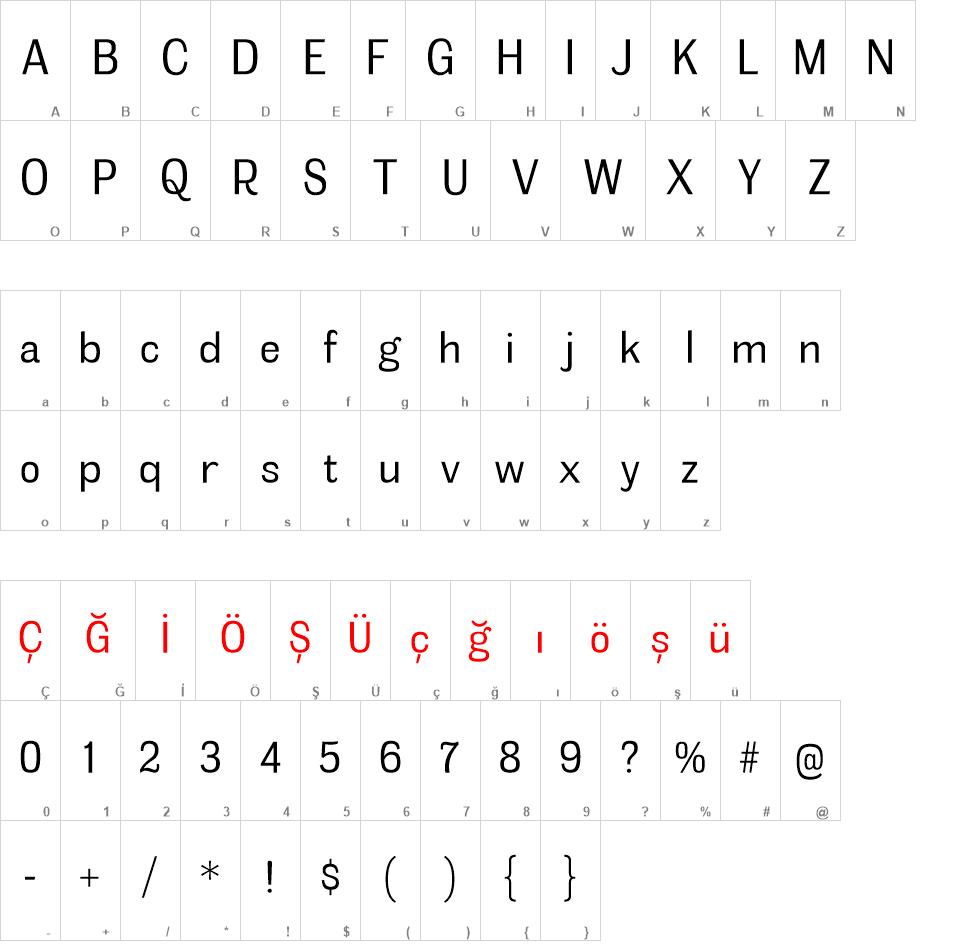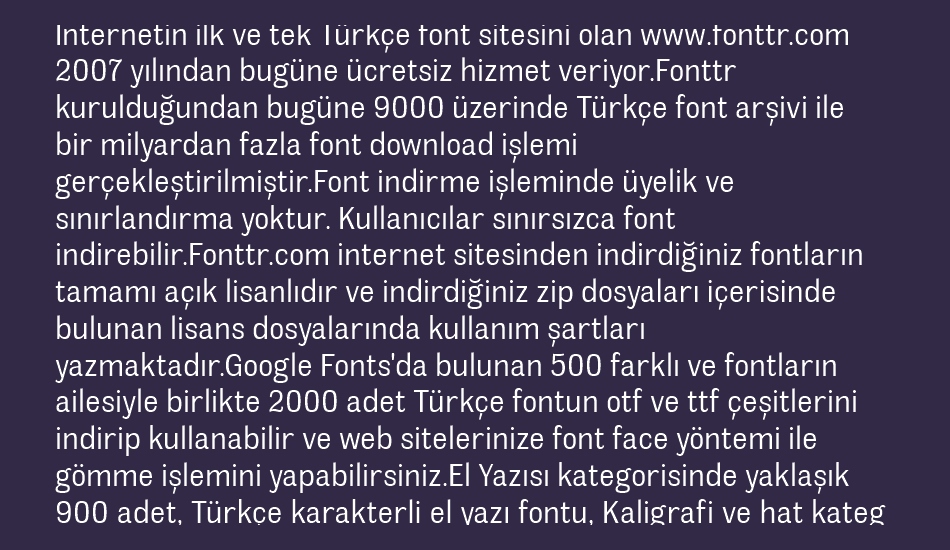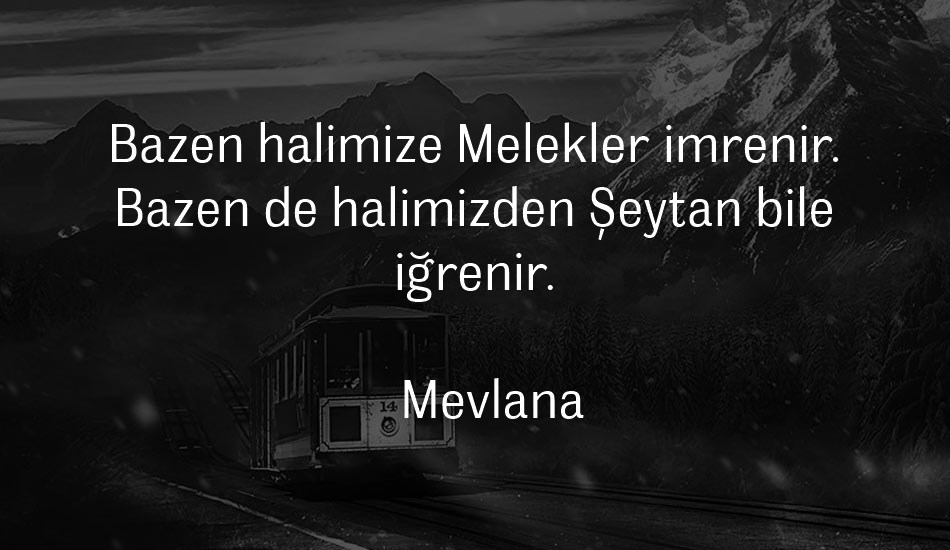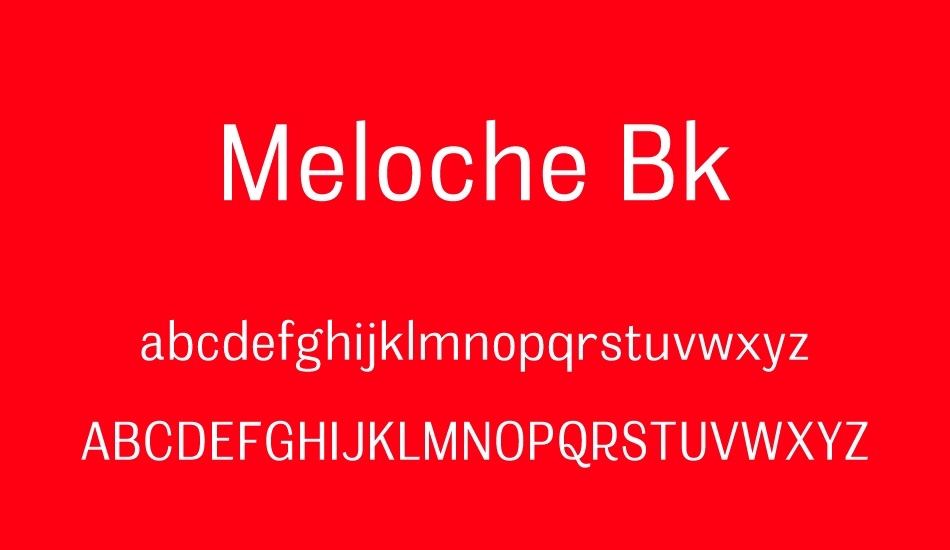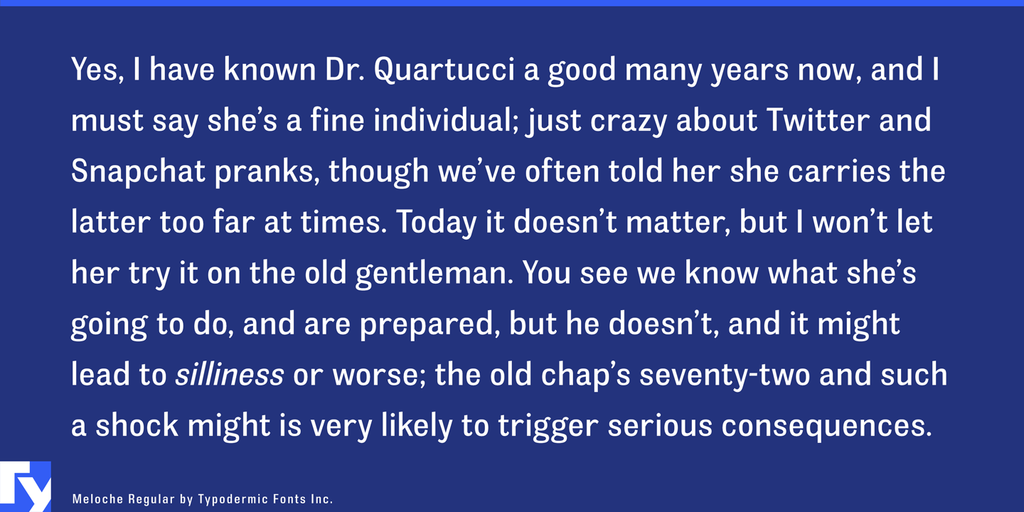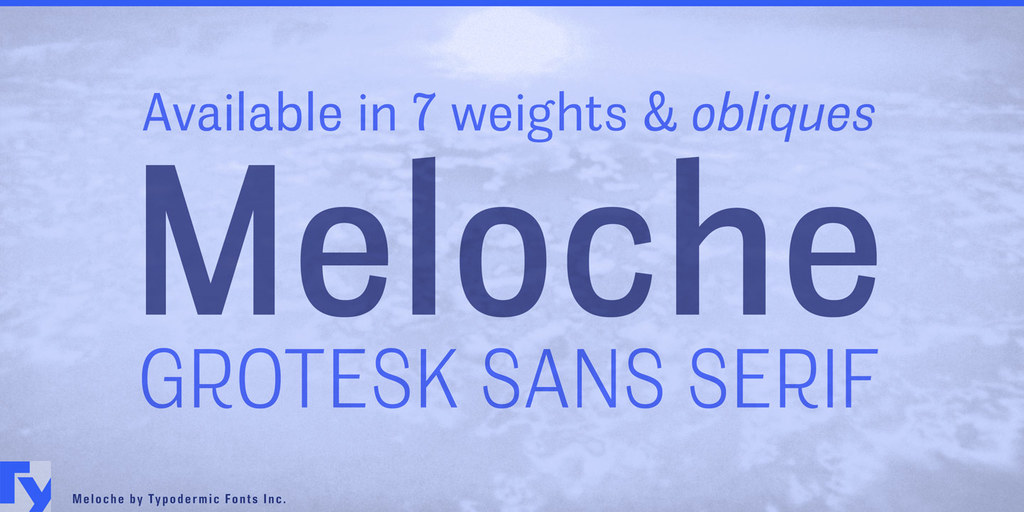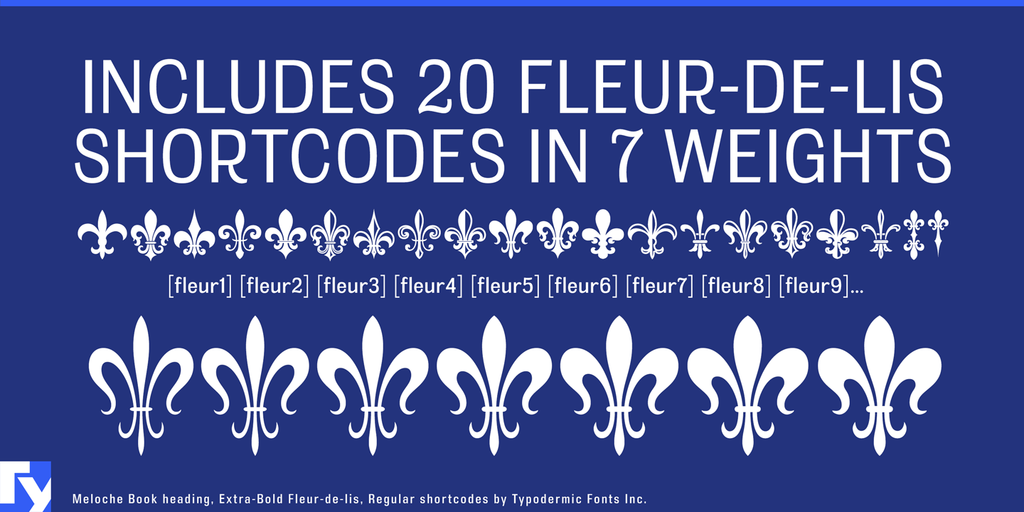
Meloche Font font
Meloche, on dokuzuncu yüzyılın sonlarında elle boyanmış Fransız işaretlerinden etkilenen eşsiz grotesk sans serif bir yazı biçimidir. 7 ağırlık ve eğri arasında bulunur. OpenType özellikleri, sayısal ordinalleri, kesirleri, eski stil rakamlarını ve basit bir Q'yı içerir. OpenType anlayışlı uygulamalarında, [fleur1] [fleur2] [fleur3] vb kısa kodlarını girerek 20 ağırlıkça eşleşen fleur-de-lis sembolüne erişebilirsiniz. Meloche Yunan, Vietnam, Kiril, Pan-Nijeryalı ve hemen hemen tüm Latin tabanlı dilleri destekliyor.